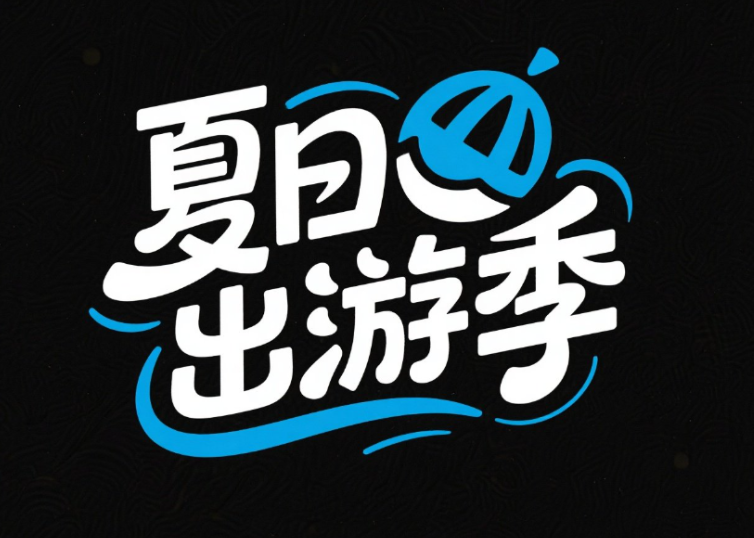
矢量插画,标志,黑色背景,白色字,创意字体设...
矢量插画,标志,黑色背景,白色字,创意字体设...AI字体提示词
创意艺术完整提示词可直接复制
风格定位
适合做风格探索与字形灵感延展。
适合场景
海报设计、品牌标题、电商设计、创意视觉
矢量插画,标志,黑色背景,白色字,创意字体设计,流畅且富有艺术感,中文”夏日出游季”,蓝色点缀。设计灵感:将字体进行抽象变形,给人以强烈的视觉冲击。高级感,扁平化,大师作品
可替换关键词
金属纸张肌理浮雕高对比立体阴影强笔触矢量插画标志黑色背景白色字
生成建议
• 先保留核心风格词,再替换材质、颜色和光影词做多轮尝试。
• 如果用于品牌标题字,补充品牌气质、行业属性和情绪关键词。
• 如果用于海报或电商标题,额外强调大字、对比度和视觉冲击力。